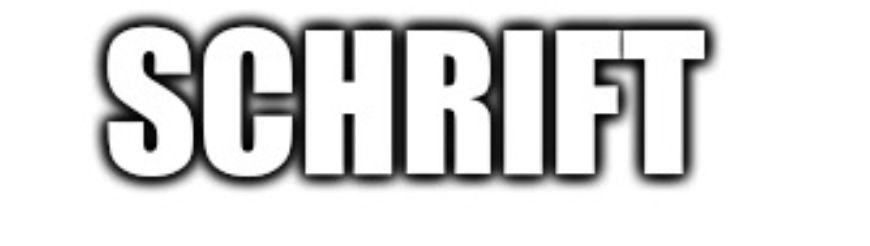
Suche Schriftart
Ich bin auf der Suche nach dieser Schriftart, die oftmals bei Memes verwendet wird.
Weiße Schrift in Großbuchstaben mit schwarzem Rand.
Kann man die irgendwo herunterladen? Bin auch nach längerer Suche nicht fündig geworden... -.-
Würde sie dann gerne via Paint.Net in vorhandene Bilder einfügen...
Kann da jemand helfen?
Hast du mal Arial in weiß mit schwarzem Rand ausprobiert? Ist doch meist eine generische, serifenlose Schrift
So eine Schrift?:
Also bei Arial wüsste ich nicht, wie ich in Paint.Net den schwarzen Rand hinzufüge...
Bin mir fast sicher, dass es Arial ist... Ggfs. Helvetica.
Halt mit entsprechenden Effekten, wie man sie jeder Schrift hinzufügen kann... Kontur, Schatten, ...
Die Schriftart heißt Impact.
Hier kann man Bilder einer Schrift hochladen und dann erkennen lassen. Wie zuverlässig das ganze ist, weiß ich allerdings nicht. Hab damit zwei mal was identifizieren können.
Die Schrift auf deinem Bild sieht aus wie: Impact
Grundsätzlich werden häufig "fette" Schriftarten verwendet wie Impact, Bebas Neue, Montserrat... zusätzlich wird dann noch eine Umrandung, Schatten oder andere Effekte dazu gewählt.
Man nehme den Text in Schwarz, als Text-Objekt. Das klebe man ein und schiebe es 1px oder 2px nach oben. und nun wiederholt man das 1 rundum - also 8 Schichten in die halben und ganzen Himmelsrichtungen. Nun den Text in Weiß in die Mitte - Tadaaaa!
Uralter Scherz als es keine Schattenfunktion wie in WordArt gab. Kann man teil lustige Dinge mit machen. Etwas Grauen Text 2px, Schwarzen 1px schieben 😇